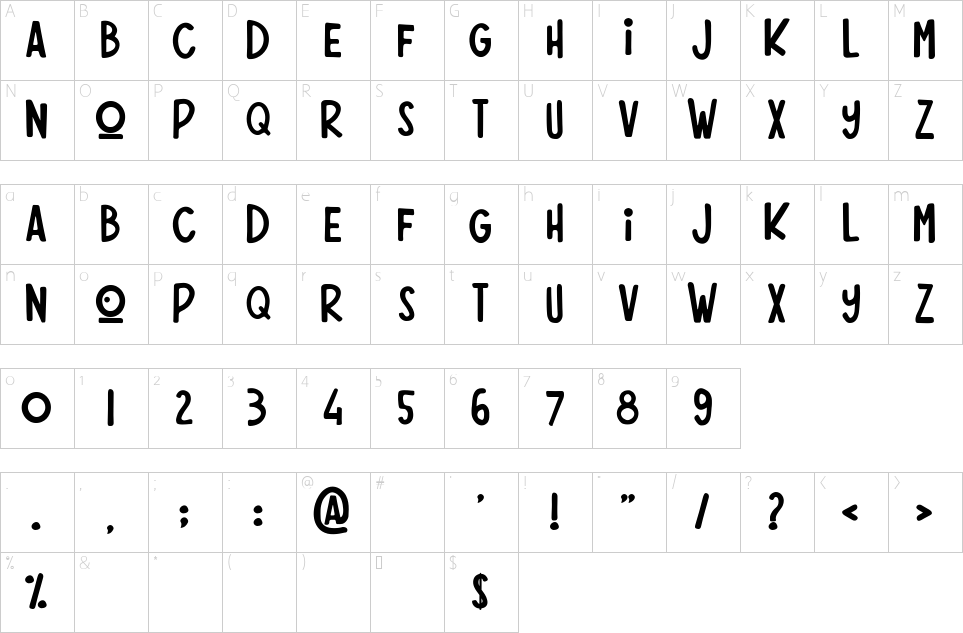
A Pina Colada Creation é uma fonte que combina um toque suave e descontraído à sua tipografia, ideal para criar gráficos em estilo descontraído ou para personalizar seu website de forma mais casual. Desenvolvida pela Octotype, essa fonte livre é uma delícia para quem procura uma solução que combine facilidade de uso com um visual atraente. Com apenas 1,965 downloads, a Pina Colada Creation já ganhou muitos fãs por seu charme e simplicidade. Seja você um designer de loja de vinhos e petiscos, ou simplesmente alguém que valoriza uma fonte que reflete seu estilo pessoal, a Pina Colada Creation é uma escolha perfeita. Descubra por si mesmo o prazer em criar com essa fonte, que traz um toque de descontração à sua escrita digital. Não hesite em dar uma chance à Pina Colada Creation para sua próxima criação visual.